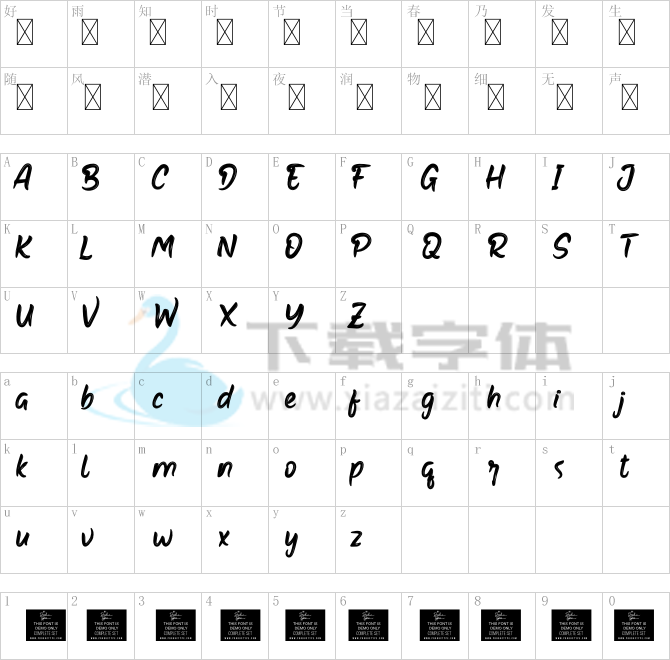
Abreact Personal.otf字体下载,这款字体结构工整、笔画清晰,兼顾美观与易读性,适用于标题、正文、海报、包装、LOGO 等多种场景。字形优雅稳定,风格百搭耐看,适配日常排版与创意设计,让文字呈现更舒适、更具质感。Abreact Personal.otf字体下载一笔一画,皆是细节,以均衡的比例、流畅的线条打造舒适视觉体验,字形端正大气,风格简约现代。无论是商业设计、品牌宣传还是日常排版,都能轻松驾驭,让文字更有格调与力量。Abreact Personal.otf字体下载字体下载。